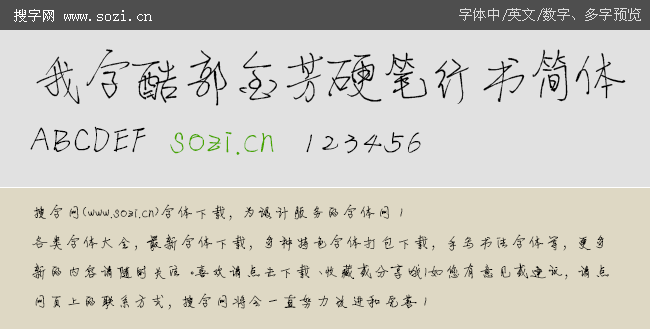
我字酷郭金芳硬筆行書簡(jiǎn)體
搜字網(wǎng)提供一款我字酷郭金芳硬筆行書簡(jiǎn)體中文書法字體下載,我字酷郭金芳硬筆行書簡(jiǎn)體是一款非常漂亮的手寫風(fēng)格書法字體,字體書寫流暢,整體字形瀟灑大方,適合應(yīng)用于廣告設(shè)計(jì)、名片設(shè)計(jì)、包裝印刷、海報(bào)設(shè)計(jì)等應(yīng)用。